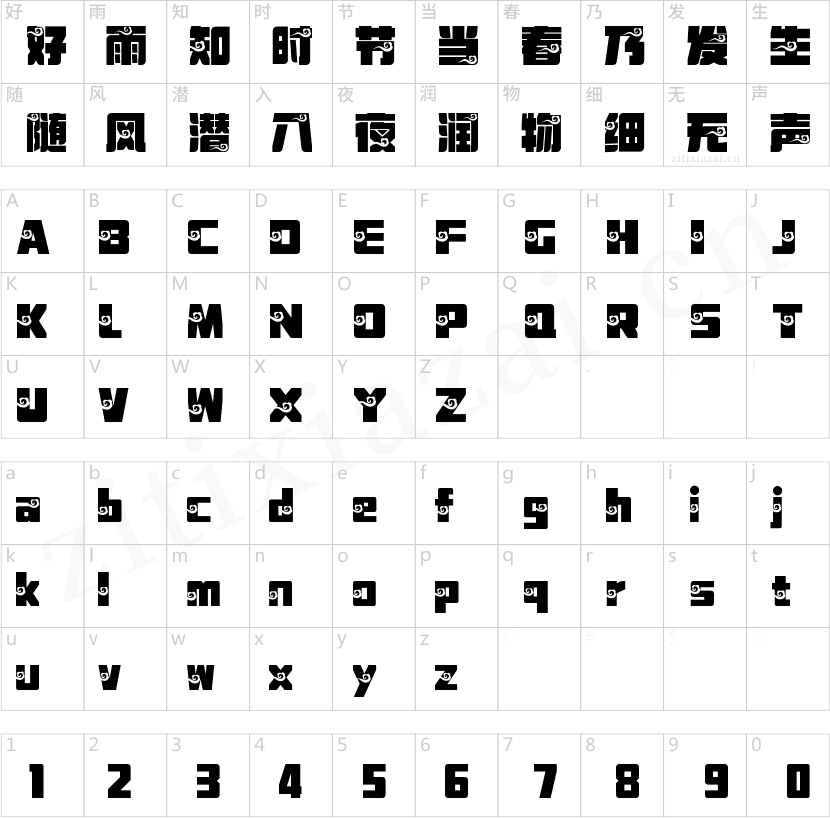
字魂祥云体
字魂祥云体,这款字体结构工整、笔画清晰,兼顾美观与易读性,适用于标题、正文、海报、包装、LOGO 等多种场景。字形优雅稳定,风格百搭耐看,适配日常排版与创意设计,让文字呈现更舒适、更具质感。字魂祥云体一笔一画,皆是细节,以均衡的比例、流畅的线条打造舒适视觉体验,字形端正大气,风格简约现代。无论是商业设计、品牌宣传还是日常排版,都能轻松驾驭,让文字更有格调与力量。字魂祥云体字体下载。
字魂字体字魂祥云体字体是由字魂创意字库设计并生产的一款可商用的字体,被收录于字魂先锋系列。该字体支持GB-2312标准,包含6942个中文、字母、符号和数字,字体类型偏向黑体,具有中国风的风格,在市面上广泛用于广告、标题字、标题等场景。